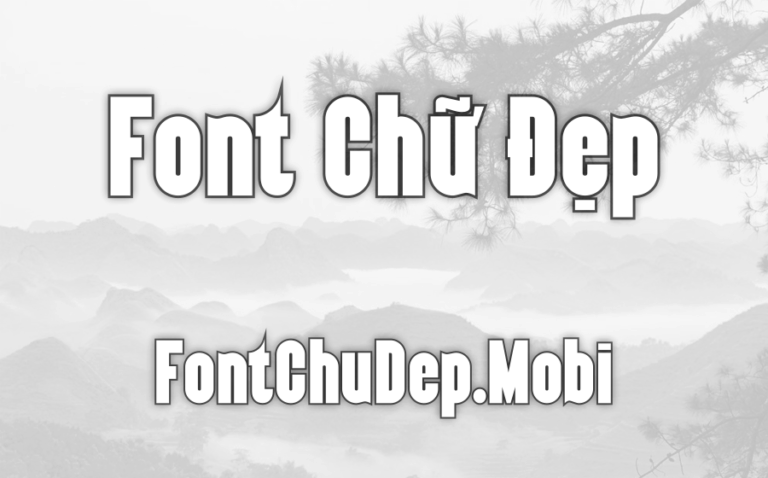
Font UVF Assassin là một lựa chọn đáng chú ý trong thế giới font chữ sans-serif hiện đại, nổi bật với phong cách táo bạo và đầy cá tính. Các đường nét sắc nét và thiết kế độc đáo của font này mang đến một cảm giác sôi động và tiên tiến, lý tưởng cho việc áp dụng vào các dự án thiết kế như tiêu đề, poster, logo và nhiều ấn phẩm truyền thông khác. Đặc biệt, font chữ này đã được giới thiệu và chia sẻ bởi một thành viên của FontChuDep.mobi. Với UVF Assassin, bạn không chỉ đơn thuần sử dụng một font chữ, mà còn có thể trải nghiệm sự sáng tạo đột phá trong từng chi tiết thiết kế.
Font UVF Assassin Việt Hóa
UVF Assassin